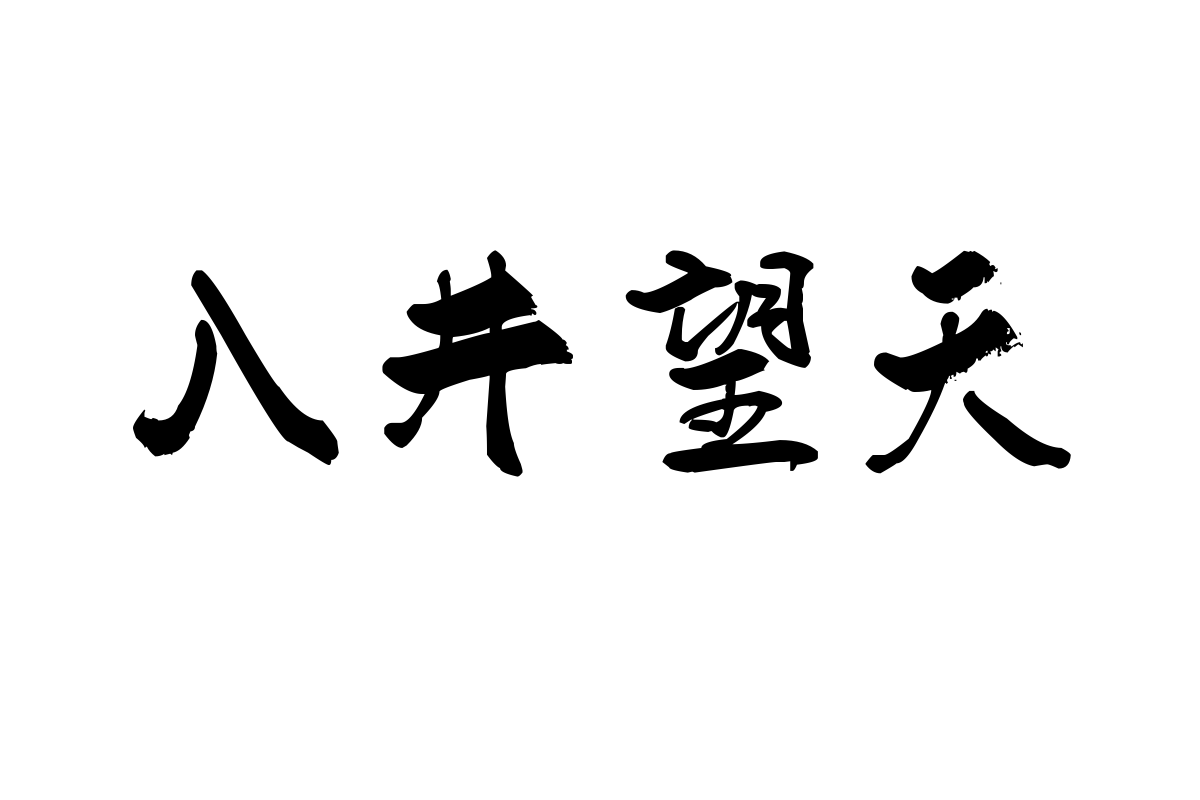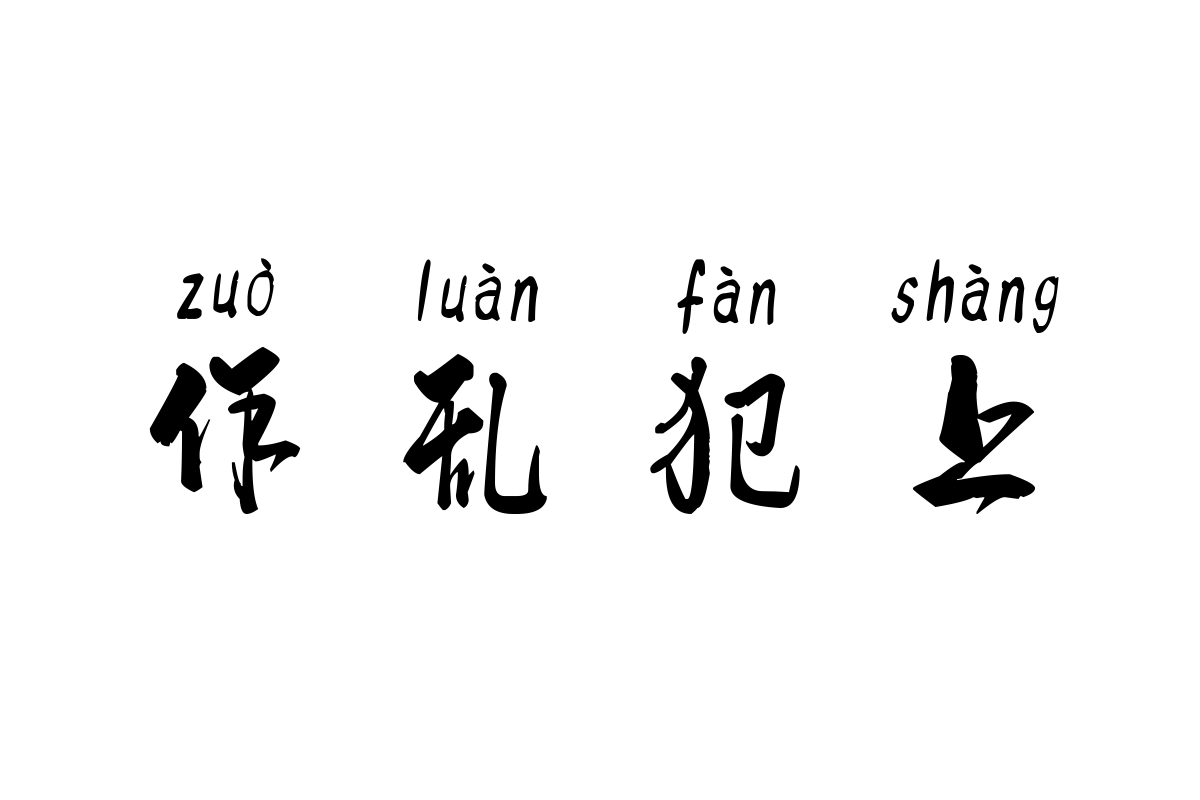
汉标清新洒脱是一款简约、现代的中文字体,具有独特的艺术风格和视觉效果。这款字体的特点是笔画流畅,字形优美,给人一种轻松、自然的感觉。它的设计风格类似于现代艺术,线条简洁有力,结构紧凑,给人以强烈的视觉冲击力。
这款字体适用于各种需要展示现代、简约风格的设计项目,如网页设计、平面设计、广告宣传等。它能够很好地与现代、简约的设计风格相融合,为设计作品增添一份清新、洒脱的气息。
汉标清新洒脱的字体特点如下:
1. 笔画流畅:字体的笔画线条流畅自然,没有过多的装饰和修饰,给人一种简洁、大方的感觉。
2. 字形优美:字体的字形优美,线条柔和,给人一种舒适、轻松的感觉。
3. 结构紧凑:字体的结构紧凑,笔画之间的间距适中,整体看起来整齐、有序。
4. 风格现代:字体的设计灵感来源于现代艺术,线条简洁有力,结构紧凑,给人一种强烈的视觉冲击力。
5. 易于阅读:字体的笔画粗细适中,易于阅读和辨识,适合用于各种需要清晰、易读的场合。
汉标清新洒脱体的笔画粗细适中,线条流畅,给人一种轻松愉悦的感觉。它的字形结构紧凑,但不失优雅,能够很好地展现汉字的美感。在排版设计中,这款字体能够很好地与各种元素融合,创造出一种和谐、自然的视觉效果。
此外,汉标清新洒脱体还具有一定的可读性,无论是用于标题、正文还是装饰性文字,都能够很好地传达出清晰、易懂的信息。这使得它在各类设计作品中得到了广泛的应用,如杂志、海报、网页等。
总的来说,汉标清新洒脱体是一款非常适合现代设计风格的中文字体,它以其独特的魅力和实用性,成为了设计师们常用的字体之一。